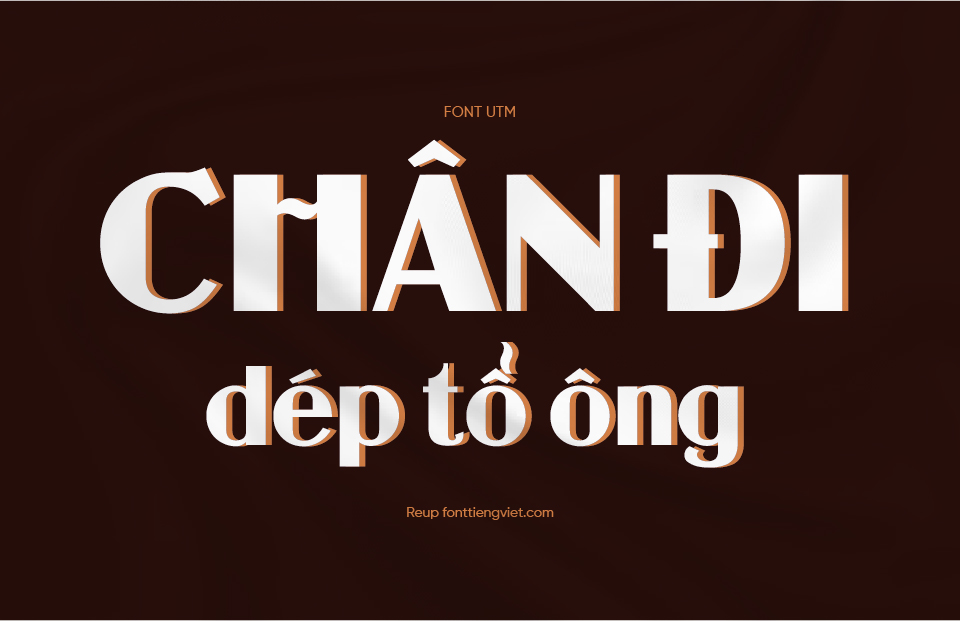
Khám Phá Sức Hút Của Font Việt Hóa UTM Guanine Trong Thiết Kế
Trong thế giới thiết kế đồ họa ngày nay, việc lựa chọn một Font Chữ phù hợp có vai trò cực kỳ quan trọng trong việc truyền tải thông điệp và tạo ấn tượng thị giác mạnh mẽ. Đặc biệt, với các dự án cần sự tinh tế và mang đậm dấu ấn Việt Nam, việc tìm kiếm những bộ font được Việt hóa hoàn chỉnh là điều không thể thiếu. Trong số đó, Font Việt Hóa UTM Guanine đã nhanh chóng trở thành một cái tên nổi bật, được nhiều nhà thiết kế và người dùng yêu thích bởi vẻ đẹp độc đáo, khả năng ứng dụng cao và sự hỗ trợ tiếng Việt tối ưu. Bài viết này sẽ đi sâu khám phá những lý do vì sao UTM Guanine lại có sức hút mạnh mẽ đến vậy và cách nó nâng tầm các sản phẩm thiết kế của bạn.
Font Việt Hóa UTM Guanine: Tại Sao Lại Là Lựa Chọn Hàng Đầu?
Font Việt Hóa UTM Guanine không chỉ là một bộ font thông thường; nó là sự kết hợp hoàn hảo giữa nét hiện đại và sự tinh tế trong từng đường nét, được thiết kế đặc biệt để tương thích với tiếng Việt. Sự tỉ mỉ trong quá trình Việt hóa đảm bảo rằng tất cả các dấu tiếng Việt đều hiển thị một cách chính xác, hài hòa, không bị lỗi hay gãy nét, điều mà nhiều font nước ngoài thường gặp phải. Điều này giúp các nhà thiết kế tự tin hơn khi sử dụng font này cho các dự án yêu cầu tính chuyên nghiệp và độ chính xác cao.
Một trong những lý do khiến UTM Guanine được ưa chuộng là sự đa dạng trong phong cách. Dù mang vẻ ngoài mạnh mẽ, hiện đại, font này vẫn giữ được sự mềm mại cần thiết, giúp nó phù hợp với nhiều loại hình thiết kế khác nhau, từ tiêu đề báo chí, logo thương hiệu cho đến nội dung văn bản dài. Khả năng đọc dễ dàng là một ưu điểm lớn, đặc biệt quan trọng đối với các ấn phẩm in ấn và nội dung kỹ thuật số.
Những Đặc Điểm Nổi Bật Của UTM Guanine
Thiết Kế Hiện Đại và Tinh Tế: UTM Guanine sở hữu những đường nét rõ ràng, mạnh mẽ nhưng không kém phần thanh lịch, mang đến vẻ ngoài chuyên nghiệp và hiện đại cho mọi tác phẩm.
Hỗ Trợ Tiếng Việt Toàn Diện: Đây là điểm cộng lớn nhất, đảm bảo hiển thị đúng và đẹp tất cả các ký tự tiếng Việt, bao gồm dấu thanh và các ký tự đặc biệt, giúp nội dung trở nên hoàn chỉnh và dễ đọc.
Tính Đa Dụng Cao: Font này có thể được sử dụng trong nhiều ngữ cảnh khác nhau, từ thiết kế đồ họa, quảng cáo, báo chí, website cho đến các tài liệu học thuật và văn phòng.
Dễ Đọc: Với cấu trúc rõ ràng và khoảng cách chữ hợp lý, UTM Guanine đảm bảo khả năng đọc tốt ngay cả ở kích thước nhỏ, làm tăng trải nghiệm người dùng.
Ứng Dụng Rộng Rãi Của Font Việt Hóa UTM Guanine Trong Đời Sống Và Thiết Kế
Không chỉ dừng lại ở mặt lý thuyết, Font Việt Hóa UTM Guanine đã chứng minh giá trị của mình qua hàng loạt các ứng dụng thực tế. Trong lĩnh vực xây dựng thương hiệu, font này thường được chọn để thiết kế logo, bộ nhận diện thương hiệu, mang lại cảm giác mạnh mẽ, đáng tin cậy và chuyên nghiệp. Các ấn phẩm quảng cáo, poster, banner cũng trở nên thu hút hơn nhờ vào sự rõ ràng và phong cách đặc trưng của UTM Guanine.
Đối với ngành xuất bản và báo chí, font này là lựa chọn lý tưởng cho tiêu đề, phụ đề và thậm chí là nội dung chính, giúp tạo ra một bố cục trang rõ ràng, dễ đọc và chuyên nghiệp. Trong kỷ nguyên số, UTM Guanine cũng rất được ưa chuộng cho thiết kế website, giao diện ứng dụng di động, các bài đăng trên mạng xã hội, đảm bảo tính nhất quán về mặt hình ảnh và khả năng hiển thị tốt trên mọi thiết bị.
Hơn nữa, trong môi trường học đường, các tài liệu ôn thi, bài giảng hay các ấn phẩm dành cho học sinh, sinh viên cũng có thể tận dụng vẻ đẹp và tính dễ đọc của font này để truyền tải thông tin một cách hiệu quả nhất. Sự dễ đọc của nó rất quan trọng cho các tài liệu học tập, đặc biệt là các kỳ thi tốt nghiệp quan trọng, giúp thí sinh tập trung hơn vào nội dung mà không bị phân tâm bởi phông chữ khó đọc.
Tổng kết lại, Font Việt Hóa UTM Guanine thực sự là một tài sản quý giá trong bộ sưu tập font của bất kỳ nhà thiết kế nào, từ nghiệp dư đến chuyên nghiệp. Với sự kết hợp giữa nét hiện đại, tính thẩm mỹ cao và khả năng hỗ trợ tiếng Việt hoàn hảo, nó không chỉ giúp các tác phẩm trở nên chuyên nghiệp hơn mà còn góp phần bảo tồn và phát huy vẻ đẹp của ngôn ngữ Việt trong thiết kế. Nếu bạn đang tìm kiếm một Font Chữ chất lượng để nâng tầm các dự án của mình, UTM Guanine chắc chắn là một lựa chọn không thể bỏ qua. Hãy trải nghiệm và cảm nhận sự khác biệt mà bộ font này mang lại cho công việc sáng tạo của bạn.